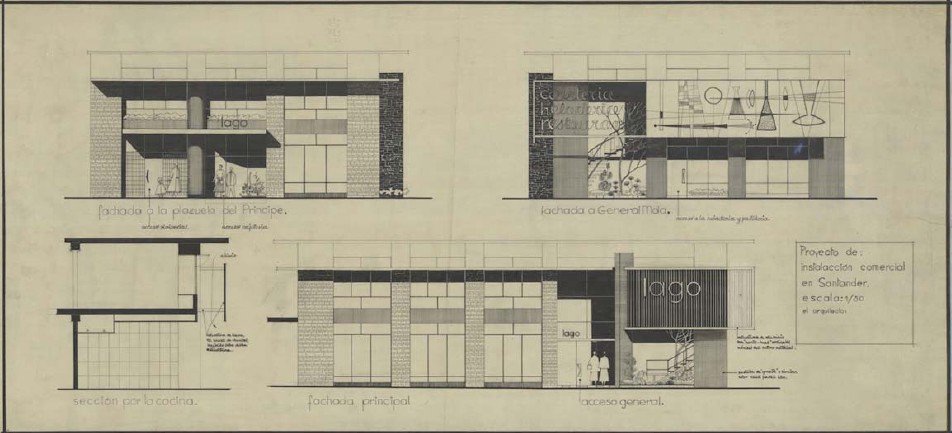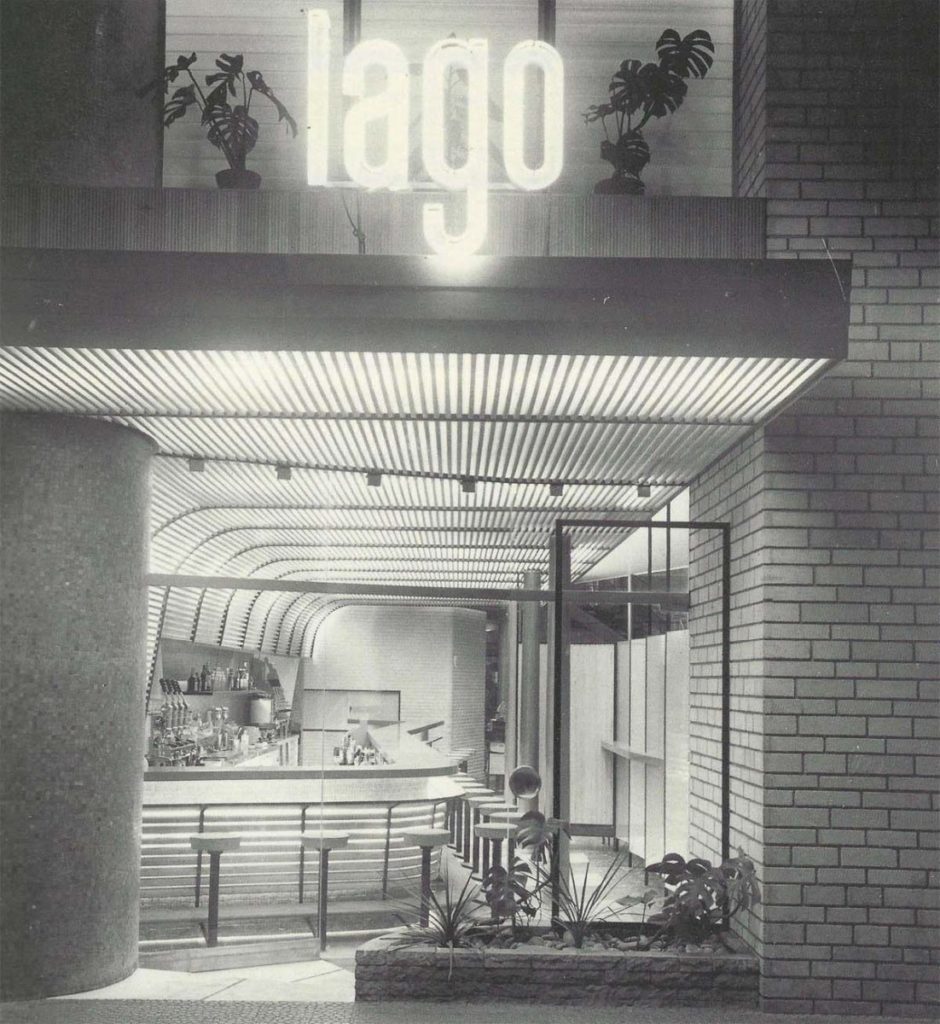
Cafetería Lago
Gracias al Archivo Mazo, podemos volver a ver el rótulo de la Cafetería Lago, que proyectó Ricardo Lorenzo en los años 50 del pasado siglo.
Con esta iniciativa, queremos seguir recuperando el pasado tipográfico de Santander y darle la vida que tuvieron antaño estos rótulos de nuestras calles.